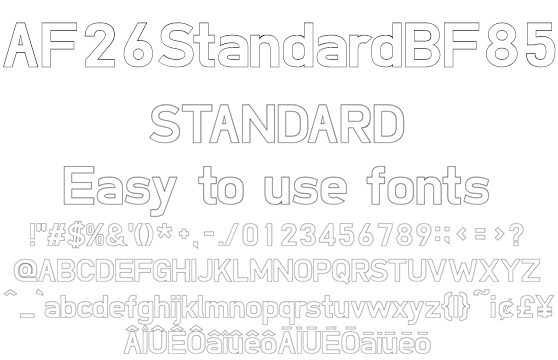
本文と見出しに使える欧文フォント AF26StandardBF85
AF26StandardBF85
読みやすく、扱いやすいボールドウエイトのスタンダードサンセリフ欧文フォント、やや強めのカーニングでお洒落で本格的なデザインに利用できます。デザインを崩す事なく隙間なポジションに配置できるよう、「AF25StandardB」に85%まで扁平を加え少々のデザイン変更と袋文字化を施しました。パンフレット、リーフレット、フライヤー、ファッション系コンテンツに最適です。日本のローマ字表記で使われる訓令式やヘボン式で扱う Ô や Ō を収録、人名地名へのアプローチもリアルです。